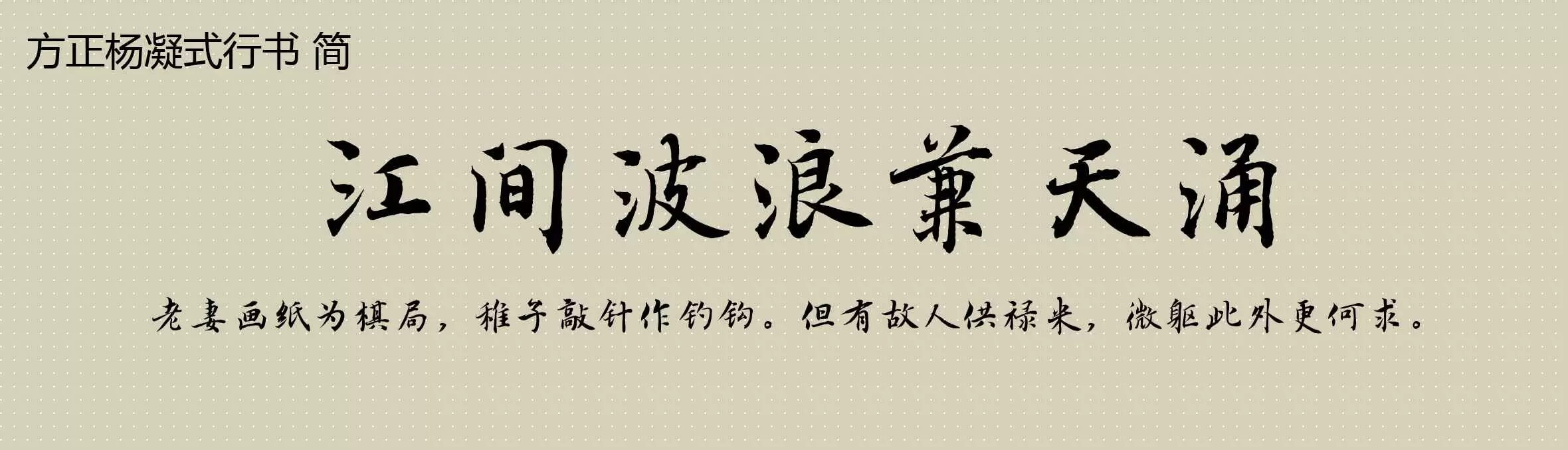
方正杨凝式行书以杨凝式《韭花帖》为临创开发依据,字体点画生动,结构端稳,风神简静;结体妍丽,整体端庄而温雅;笔法巧妙,用笔一丝不苟却毫无古板呆滞之感,文人之气十足。应用场景:电商、品牌、海报、杂志、书籍、包装、广告、招牌、新媒体、影视、动漫等。
杨凝式(873~954年),字景度,号虚白,华州华阴(今陕西华阴)人。唐末五代时期宰相、书法家。在书法历史上历来被视为承唐启宋的重要人物。“宋四家”都深受其影响。代表作品有《韭花帖》、《卢鸿草堂十志图跋》、《神仙起居法》。